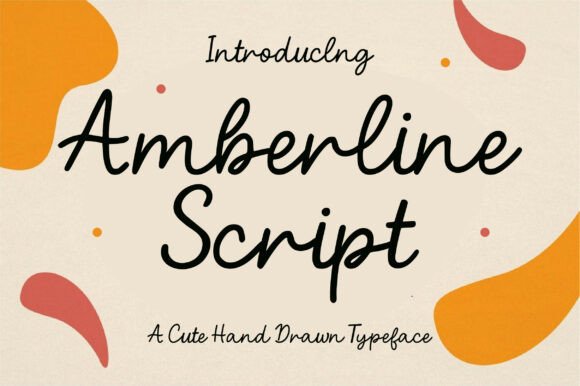
Amberline Script
適切なデザイン要素を見つけるのは難しい場合がありますが、Amberline Scriptは作品を即座に引き立てる優れたコレクションを提供します。
POD(オンデマンド印刷)製品、結婚式の招待状、またはソーシャルメディアのグラフィックを作成している場合でも、Amberline Scriptは理想的です。